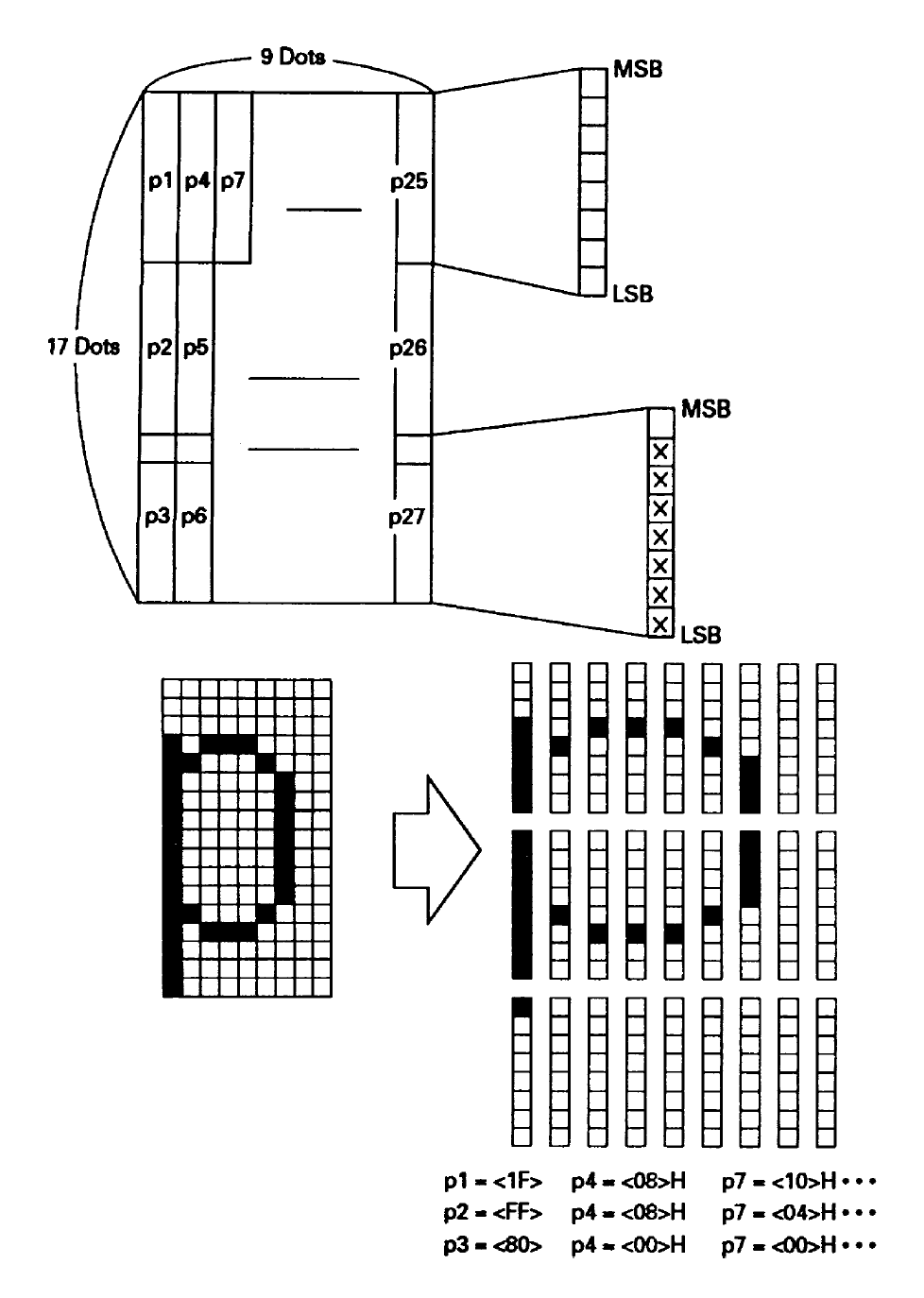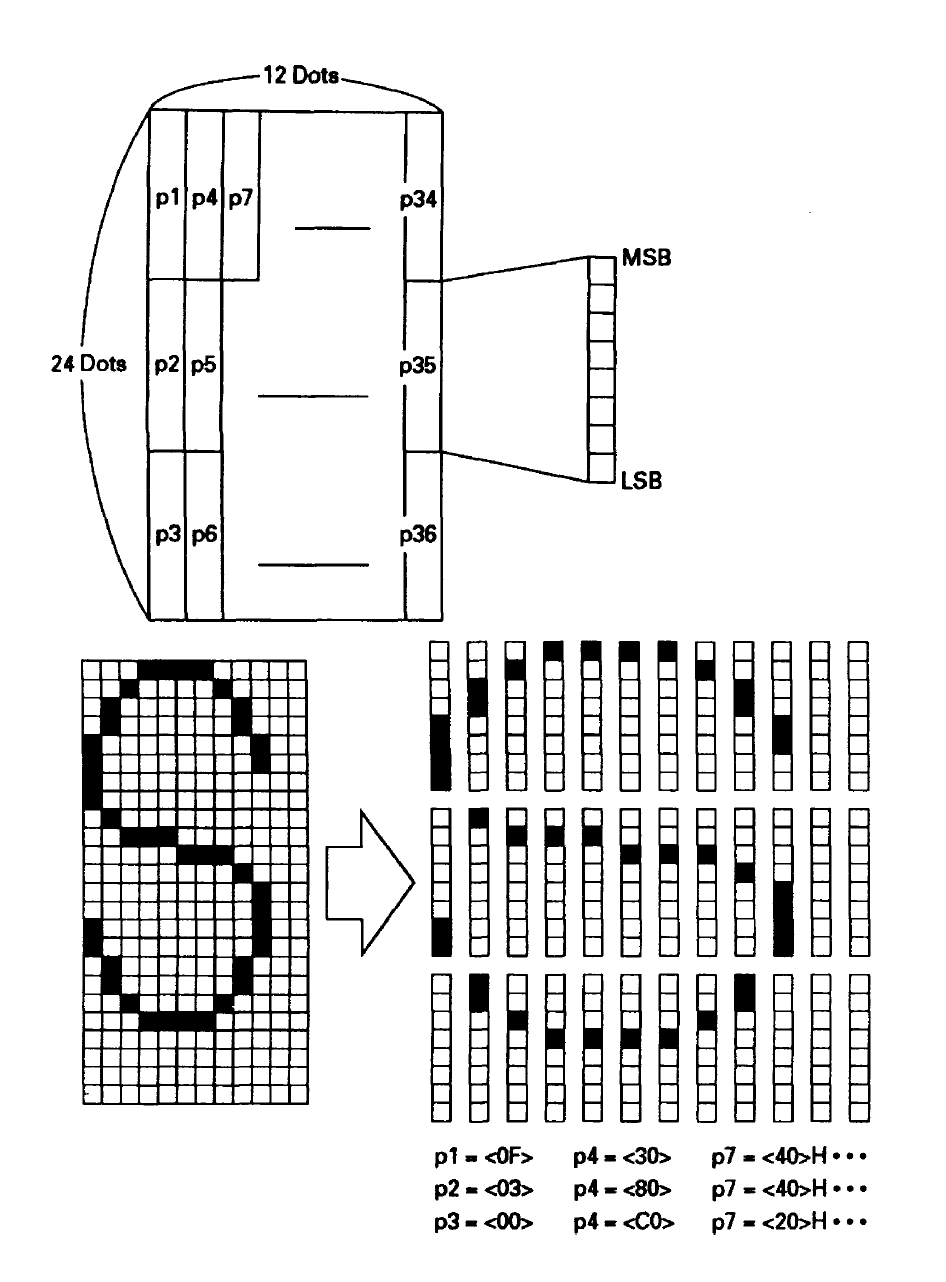
Bondrucker-Schrift zu klein
Mein Thermodrucker Citizen CBM 231 druckt sehr klein.
Kann man die Schriftgröße verändern ? Mit einem ASCII-Zeichen ?
Das Gerät verwendet Bitmap-Fonts mit definierter Höhe. Zwei Fonts stehen zur Auswahl, A mit 24 dots Höhe und B mit 17 dots Höhe. Eine Änderung der Schriftgröße kann nur über eine Verdoppelung der Höhe oder Verdoppelung von Höhe und Breite geschehen, für beides stehen die Codes in der Bedienungsanleitung. Dort her stammen auch die Abbildungen.
Specifying Collectively the Print Mode (ESC ! n)
Code: [1Bh] + [21h] + n
* {0 < n < FF} The data is described in Hex code.
Printing mode is assigned. Each n bit indicates the following:
BIT FUNCTION VALUE
4 Double height Canceled Specified
5 Double width Canceled Specified
Sollte das  so aussehen ?
[1Bh] + [21h] + 4+5
Oder:   [1Bh] + [21h] + 4   [1Bh] + [21h] + 5
Wo einfügen, am Anfang der Sequenz oder bei jeder Zeile ?